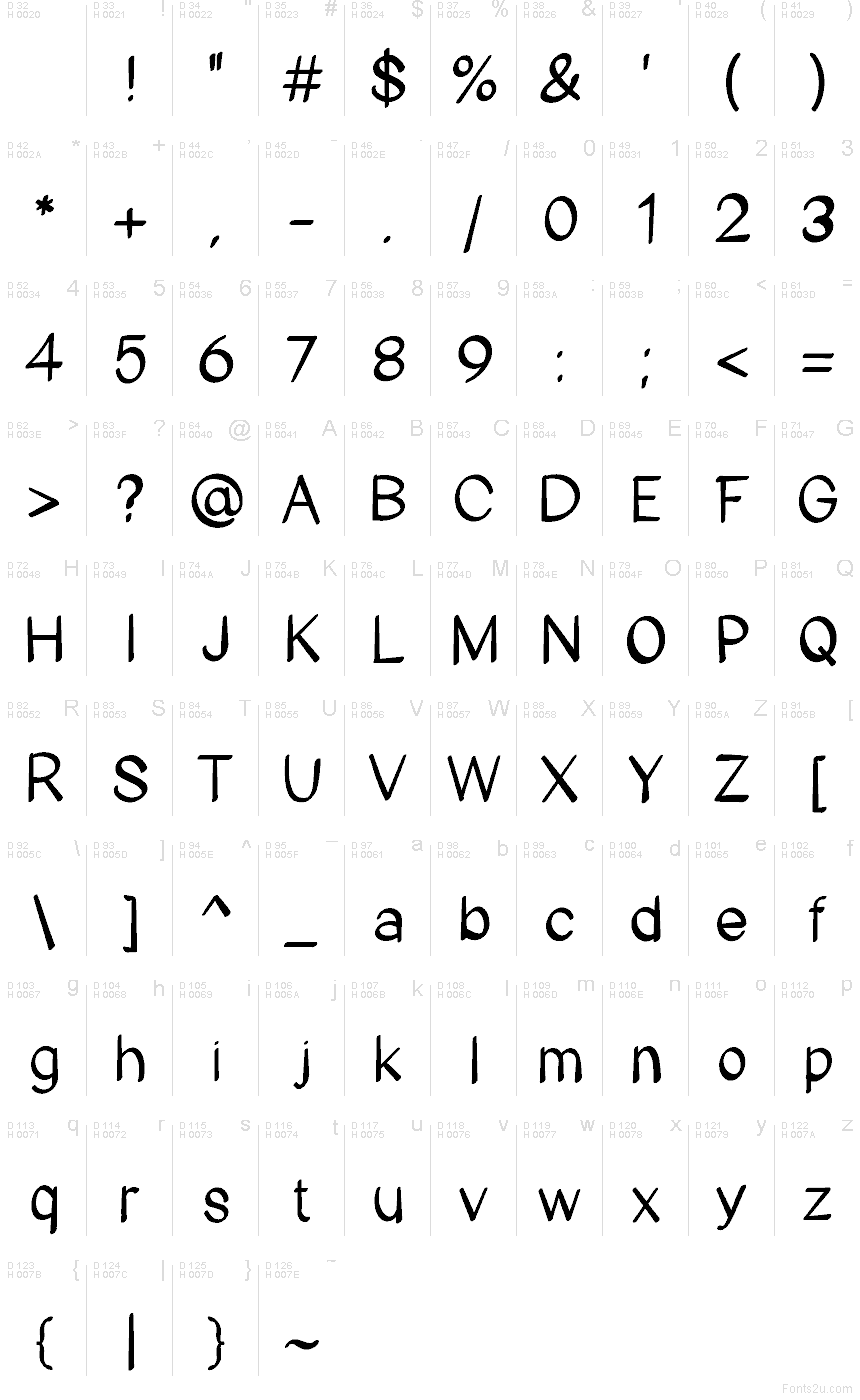
Ertelor
Ertelor é uma fonte manuscrita gratuita com traços soltos e irregulares e extremidades gentilmente arredondadas. O design das suas letras mantém um ritmo casual, feito à mão, com pequenas irregularidades que conferem ao espaçamento e às curvas um toque pessoal, fugindo do aspecto artificial.
Ertelor é uma ótima escolha para convites, frases, logotipos, embalagens, posts em redes sociais e destaques em cartazes, pois carrega o visual de uma escrita rápida e natural sem parecer descuidada. Use-a quando quiser transmitir um ar informal e direto, especialmente em textos curtos ou numa marca simples.